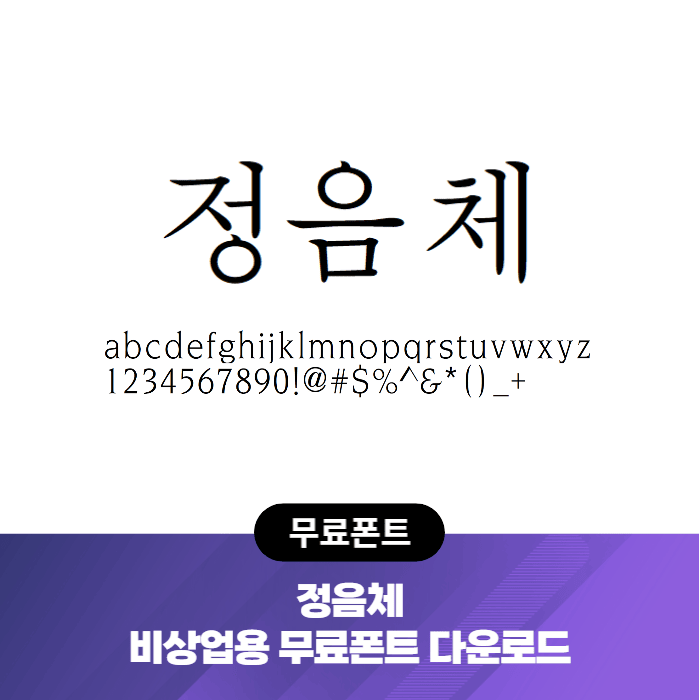
정음체
서울시스템주식회사에서 배포하는 정음체는 남과 북이 공동으로 개발한 서체입니다.남북폰트디자인교류연구원과 조선민주주의인민공화국 삼천리총회사에서 제작한 공개 글꼴입니다. 비영리로 라이선스가 정해져 있어서 상업적으로 이용은 할 수 없지만 개인적이나 비영리적으로 활용해볼 수 있습니다.
남북합작 한글서체 정음체입니다.분단으로 서로 달리써온 한글 글자꼴(폰트)이 남북의 공통 노력으로 연구 개발됐습니다.국내 민간 문자디자인연구소인 남북폰트디자인교류연구원(원장 아트디렉터 노수용)은 국내서체개발사인 서울시스템주식회사(대표 김학선), 그리고 북한 삼천리정보센터와 함께 남북이 공감 할 수있는 한글 글자체인 '정음체'를 2년의 개발기간을 들여 완성했습니다.남북 디자이너가 만나 공동으로 글꼴 통일작업을 한 것은 이번이 처음입니다.
남북의 한글 글자꼴 실무자는 중국 단둥에서 남북이 공유할 수 있는 최종 글자꼴을 확정하고 본격적인디자인 작업에 들어가 개발을 완료했습니다.양측은 완성된 글자꼴의 이름을 · '정음체'라고 붙이고 이를 무료로 보급키로 했습니다.이 글자꼴은 한글 창제원리인 상형/가획/합용의 원칙에 맞춰 우리나라의 대표적 서체인 바탕명조와 북한에서 가장 많이 사용하는 청봉체의 장점을 살려 재구성했습니다.청봉체의 붓 터치를 반영한 옛글자와 바탕명조의 디지털 폰트 이미지를 혼합한 것입니다.힘차고 강한 민족의 미래지향적 희망을 상징한 게 특징입니다.